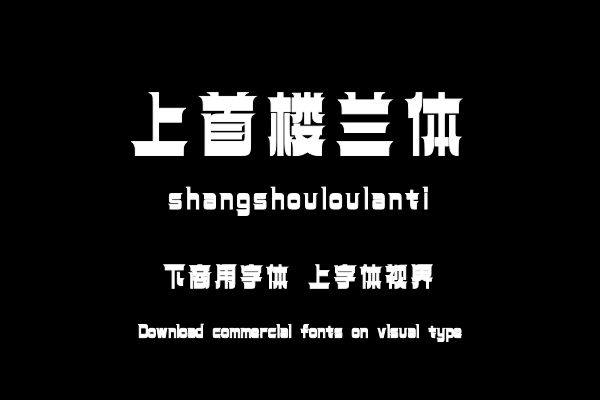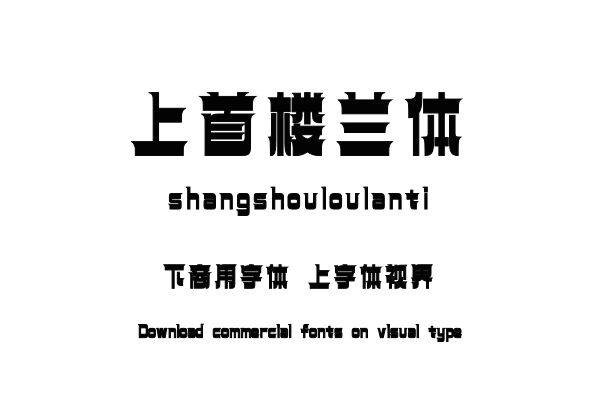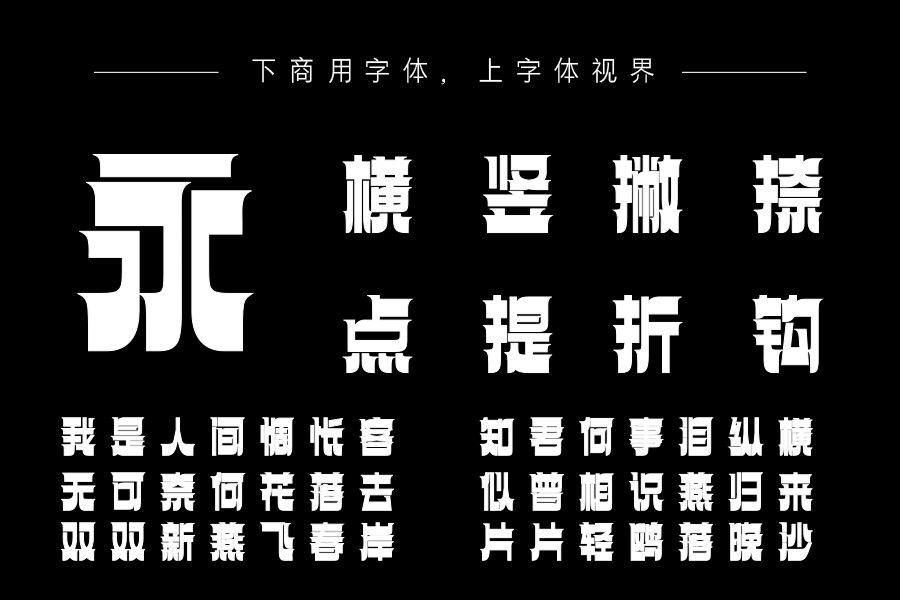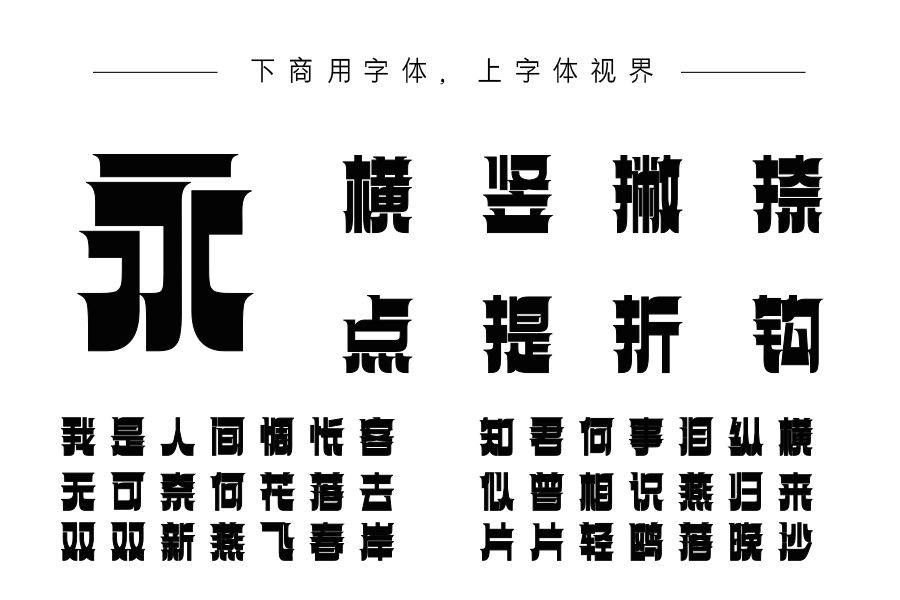
上首楼兰体,笔画中以末端细削而锐利构成,加强了字的个性和视觉冲击力。线条之间的粗细变化不一,更显字形轮廓感。字体整体风格颇有楼兰古城风范,严谨的构体使视觉明快,......购买须知:“下载服务费”与“字体VIP”所获得字体 仅用于个人非商用, 商用请联系付费授权。本字体为电脑用字,手机没有root权限不支持直接手机换字(手机如何root,请自行百度搜索教程)。购买前请先 了解清楚后再付款 ,字体为虚拟产品无法回收 一旦购买不支持退款。